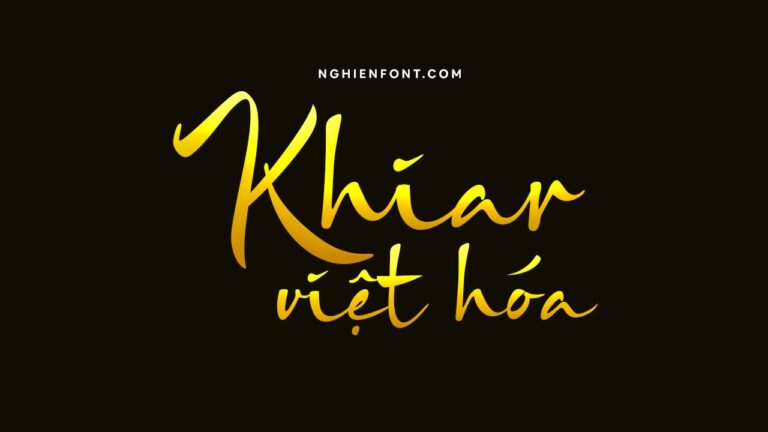
LNTH Khiara Script là một font chữ viết tay sang trọng và thời trang. Đó là sự lựa chọn hoàn hảo cho việc xây dựng thương hiệu và dự án logo, bao bì sản phẩm, trích dẫn, thiệp mời.
Phông chữ này được mã hóa PUA, nghĩa là bạn có thể truy cập tất cả các nét tượng hình và dấu gạch ngang một cách dễ dàng!